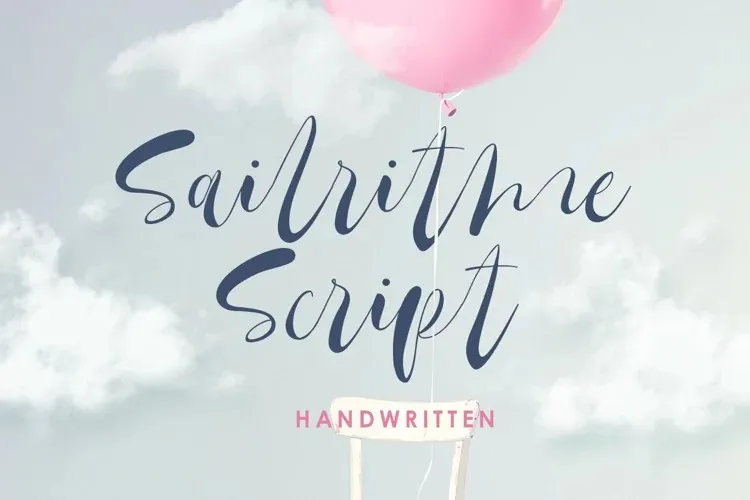
A Sailritme Font é uma delicada mistura de script moderno com traços manuscritos e caracteres decorativos. Ela traz uma sensação de elegância que se tornou sua principal característica, especialmente acentuada por um rótulo dançante sobre o qual todos os caracteres flutuam. Esta font foi projetada para atender aos mais altos padrões de formatura, idealmente para ser aplicada em criações como logomarcas, cartas de convite, selos, logos, revistas e livros, desde até as caixas de embalagens dos produtos de moda ou a estilização de maquiagem. Seu design prático também é perfeito para cartões de aniversário ou casamento, notícias de jornais e editoriais, adesivos, papelaria e até mesmo para gráficos publicitários em vários formatos. A cada uso, ela cria uma atmosfera sofisticada e elegante que certamente deixará seus projetos inconfundíveis e altamente profissionais.